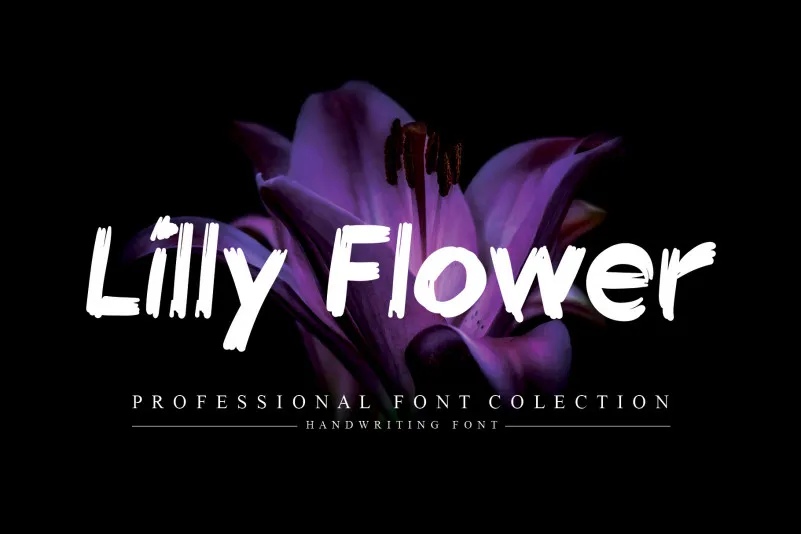
Lilly Flower Brush Font – Download Grátis
A fonte Lilly Flower Brush é um tipo de tipo expressivo e único, criado para quem busca uma cara moderna na sua próxima criação. Esse design foi feito para atender aqueles que desejam dar um toque especial a seus designs, seja em logotipos ou letras no site. Com linhas grossas e uma tendência marcante, Lilly Flower Brush é ideal para adicionar um toque de elegância ao seu layout. É perfeito para qualquer designer gráfico buscando uma fonte que ofereça uma mistura sofisticada e moderna. Não apenas elevará o nível do seu design, mas também será um destaque na página. Essa fonte foi criada pelo designer andikastudio, um nome que você pode confiar em produzir recursos de alta qualidade para designers como você. Seja para um site de moda minimalista ou uma identidade visual de uma marca sofisticada, Lilly Flower Brush está pronta para tornar suas criações únicas ainda mais belas e atraentes.